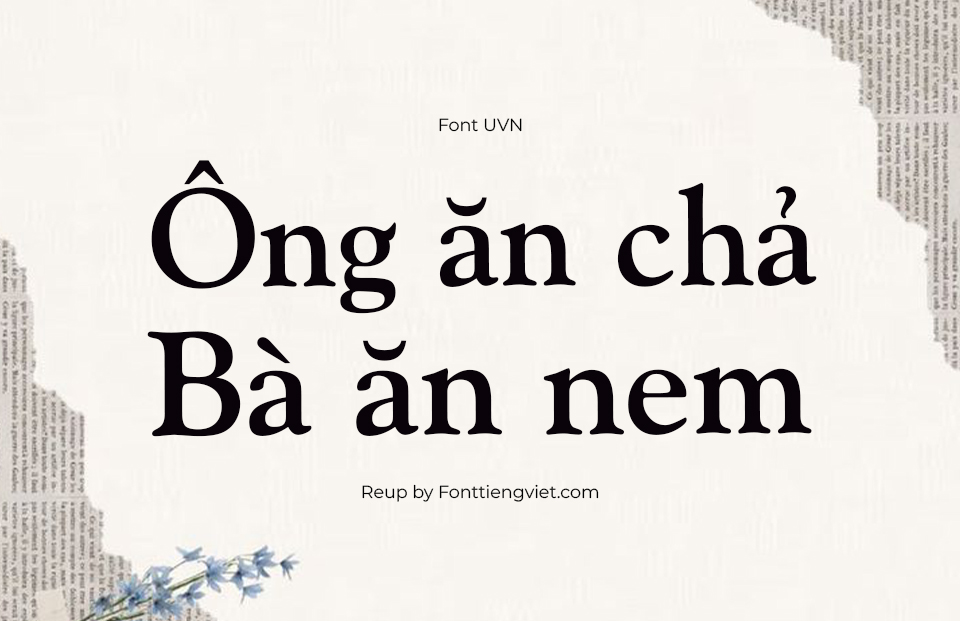
Giới thiệu về Font Việt Hóa UVN Giong Song
Trong thế giới đồ họa, việc lựa chọn một Font Chữ phù hợp đóng vai trò quyết định đến tính thẩm mỹ của sản phẩm. Font Việt Hóa UVN Giong Song là một trong những bộ phông chữ độc đáo thuộc hệ thống UVN, nổi tiếng với phong cách mềm mại và uyển chuyển như những con sóng. Bộ font này đã được tối ưu hóa hoàn toàn cho bảng mã Unicode, giúp người dùng dễ dàng gõ tiếng Việt có dấu mà không lo lỗi hiển thị trên các phần mềm thiết kế phổ biến hiện nay.
Đặc điểm nổi bật của bộ font
Đúng như tên gọi, Font Việt Hóa UVN Giong Song sở hữu những đường nét uốn lượn đặc trưng, tạo cảm giác thư thái và nghệ thuật. Đây là lựa chọn lý tưởng cho các bạn học sinh, sinh viên và giáo viên khi muốn trang trí bài thuyết trình, làm thiệp chúc mừng hoặc thiết kế các tiêu đề báo tường. Sự kết hợp giữa nét thanh và nét đậm giúp văn bản trở nên sống động, thu hút thị giác nhưng vẫn đảm bảo sự chuyên nghiệp cần thiết cho môi trường học đường.
Ứng dụng thực tế và cách cài đặt hiệu quả
Hướng dẫn sử dụng trong giáo dục
Với phong cách thanh thoát, Font Việt Hóa UVN Giong Song thường được sử dụng trong các ấn phẩm mang tính truyền thống hoặc nghệ thuật. Thầy cô có thể dùng font này để làm bằng khen, giấy khen cho học sinh nhằm tăng thêm giá trị thẩm mỹ. Cách cài đặt rất đơn giản: sau khi tải về, bạn chỉ cần giải nén, nhấn chuột phải vào file font và chọn Install để bắt đầu sử dụng ngay trên máy tính của mình.
Kết luận về bộ phông chữ nghệ thuật
Nếu bạn đang tìm kiếm một giải pháp làm mới nội dung văn bản thì đây chính là lựa chọn không thể bỏ qua. Việc sở hữu Font Miễn Phí, Font Việt Hóa, Font Việt Hóa UVN Giong Song sẽ giúp các dự án sáng tạo của bạn trở nên ấn tượng và gần gũi hơn bao giờ hết. Hãy tải ngay để trải nghiệm sự khác biệt trong từng nét chữ nghệ thuật này nhé.